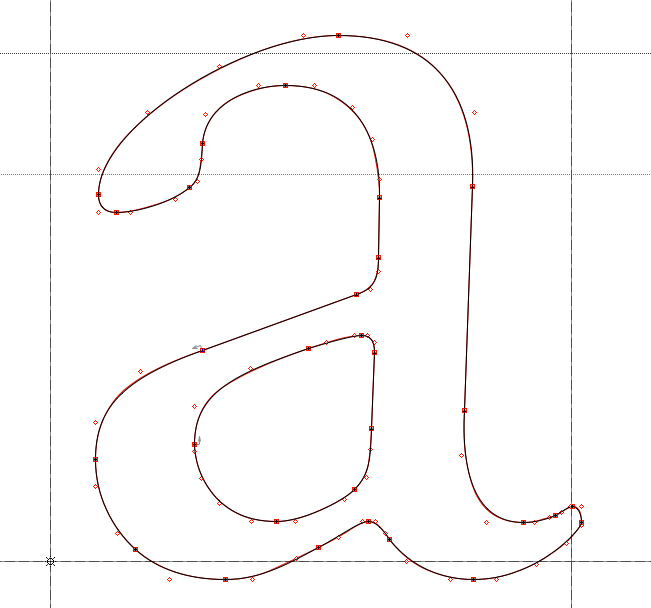
Webfont = Bildschirmschrift?
Ich arbeite gerade für einen Kunden am User-Interface Design für Touchpanels im Bereich Home Automation.
Das heißt ich gestalte die graphische Oberfläche.
Für den gleichen Kunden habe ich zuvor das Corporate Design gemacht und als Hausschrift die Accord Alternate
gewählt. Der Kunde möchte nun die Accord Alt auch auf den Touchpanels haben. Der normale OpenType-Font verpixelt
ab einer bestimmten Größe. Der Schriftenanbieter bietet aber auch einen Webfont-Satz an –> nun die Frage: Ist Webfont=Bildschirmfont bzw. macht der Einsatz von Webfonts einen sichtbaren Unterschied auf Touchpanels oder an Bildschirmen generell? Oder geht es da mehr um die Kompatibilität der Schrift im Netz?
Würde mich freuen da mehr Klarheit zu bekommen.
Ja, »Webfonts« bezieht sich vor allem auf das Lizenzierungs- bzw. Einbettungssystem der Schriften innerhalb von Webseiten. Ob die Schrift tatsächlich bildschirmoptimiert ist, steht auf einem anderen Blatt.
Und ein noch viel schwierigeres Thema ist, was »Bildschirmoptimierung« bedeutet. Da hängt es in erster Linie erstmal davon ab, welches Betriebssystem mit welchen Render-Einstellungen da benutzt wird. Das beeinflusst ganz entscheidend die Darstellung. Aus dem Begriff »Home Automation« lässt sich das natürlich nicht ableiten. Da müsste man erstmal viel mehr wissen.
Ralf, gib's ruhig zu: Die Situation ist nicht besser als im Fotosatz, wo eine Garamond auf jeder verdammten Kiste anders aussah. Das hat mit Ästhetik oder Schriftkultur nicht das Geringste zu tun, sondern stattdessen mit – Cash.
Ich bin ja immer noch sauer auf Deine ausschweifenden Belehrungen zur Qualität der Konturbeschreibungen in den sog. Vektorfonts*. PostScript ist IMNSHO deshalb besser als TrueType, weil die Kurven mittels kubischer splines beschrieben werden und nicht mit (primitiveren) quadratischen Kurven. Denk' doch mal an Deine Schulzeit zurück. Mit einem Algorithmus, der irgendwo ein ³ beinhaltet, kann man eben viel komplexere Dinge beschreiben als mit einem ². Die Konvertierung eines PostScript-Fonts in einen TrueType-Font ist mit sichtbaren Verlusten verbunden. Und so wie Bernd Möllenstedt behauptet hat, zwischen den verschiedenen Digitalisierenden Unterschiede wahrnehmen zu können, so sind die Kurven in PostScript einfach „schöner“. Guck mal, ich bin ja auch hübscher als Du. Und dann bist Du auch noch Ossi. Ich mein’, wie sollte das jetzt auch anders ausgehen …
Dass TrueType natürlich das modernere Format war und gerade in Kombination mit Windows-Maschinen und dem Web Vorteile bot, steht außer Frage. Wir hatten aber seinerzeit über die Qualität der Kurvenbeschreibung diskutiert.
* Vektorfonts deshalb nicht bzw. nicht mehr, weil keine Vektoren mehr zum Einsatz kommen. Stattdessen werden Outlines benutzt, was natürlich viel besser ist.
Wir hatten das schon aufgedröselt, aber von mir aus noch einmal: Eine stupide vollautomatische Konvertierung von PostScript zu TrueType kann tatsächlich zu Qualitätseinbußen führen – das liegt in der Natur (bzw. Mathematik) der Sache. Aber jetzt kommt das Aber: Das ist eben ein Phänomen der Konvertierung(!!!) und sagt nicht das Geringste über die Qualität der Formate an sich aus. Die PostScript-Outline kann selbstverständlich auch perfekt mit TrueType-Kurven nachgebildet werden – wenn TrueType dafür ein paar mehr Stützpunkte braucht, ist das doch völlig egal. Das sieht man der Kurve doch überhaupt nicht an! Die Qualitätsunterschiede heutiger digitaler Schriften sind gewaltig – aber das liegt in der gestalterischer Leistung der Schriftgestalter begründet, nicht im Fontformat.
Dieser Format-Krieg (und seine Mythen) sind ein Kind der 1990er, wo es darum ging, das jeweils andere Format möglichst zu verdrängen. Heute glaubt diese Märchen aber (fast) keiner mehr.
Von mir aus können wir gern eine empirische Studie durchführen, wo die Probanden gebeten werden, TrueType- und PostScript-Kurven allein am Kurven-Verlauf zu erkennen. Wenn dabei ein Ergebnis rauskommt, das besser ist die Ergebnisse von Wünschelrutengängern darfst Du mich gerne einen Lügner nennen. Bis dahin werde ich diesen Mythos von prinzipiell »schöneren« PostScript-Kurven weiterhin als Irrglauben bezeichnen.
Die Konvertierung eines PostScript-Fonts in einen TrueType-Font ist mit sichtbaren Verlusten verbunden.
ab welcher vergrößerung sind die unterschiede denn sichtbar?
Wenn die Kurven sauber aufgebaut sind, also z.B. die Stützpunkte ordentlich an den Extrempunkten sind, dann funktioniert sogar eine vollautomatische Konvertierung. Ich hab’s gerade mal zur Demonstration gemacht:
Adobe Garamond Pro als Original-PostScript-Font (schwarz). Konvertiert in FontLab zu TrueType (rot) und in Photoshop übereinander gelegt:
Das Ergebnis ist praktisch identisch. Es zeigen sich hauchfeine Unterschiede, die, wenn es denn unbedingt sein muss, mit ein paar zusätzlichen Stützpunkten* auch noch korrigiert werden könnten. Dass bestimmte Formen in PostScript »schöner« oder im TrueType gar überhaupt nicht darstellbar wären, ist einfach falsch.
*) Und jetzt bitte nicht mit dem alten Mythos kommen, dass ein paar mehr oder weniger Stützpunkte heute noch eine Rolle spielen würden.